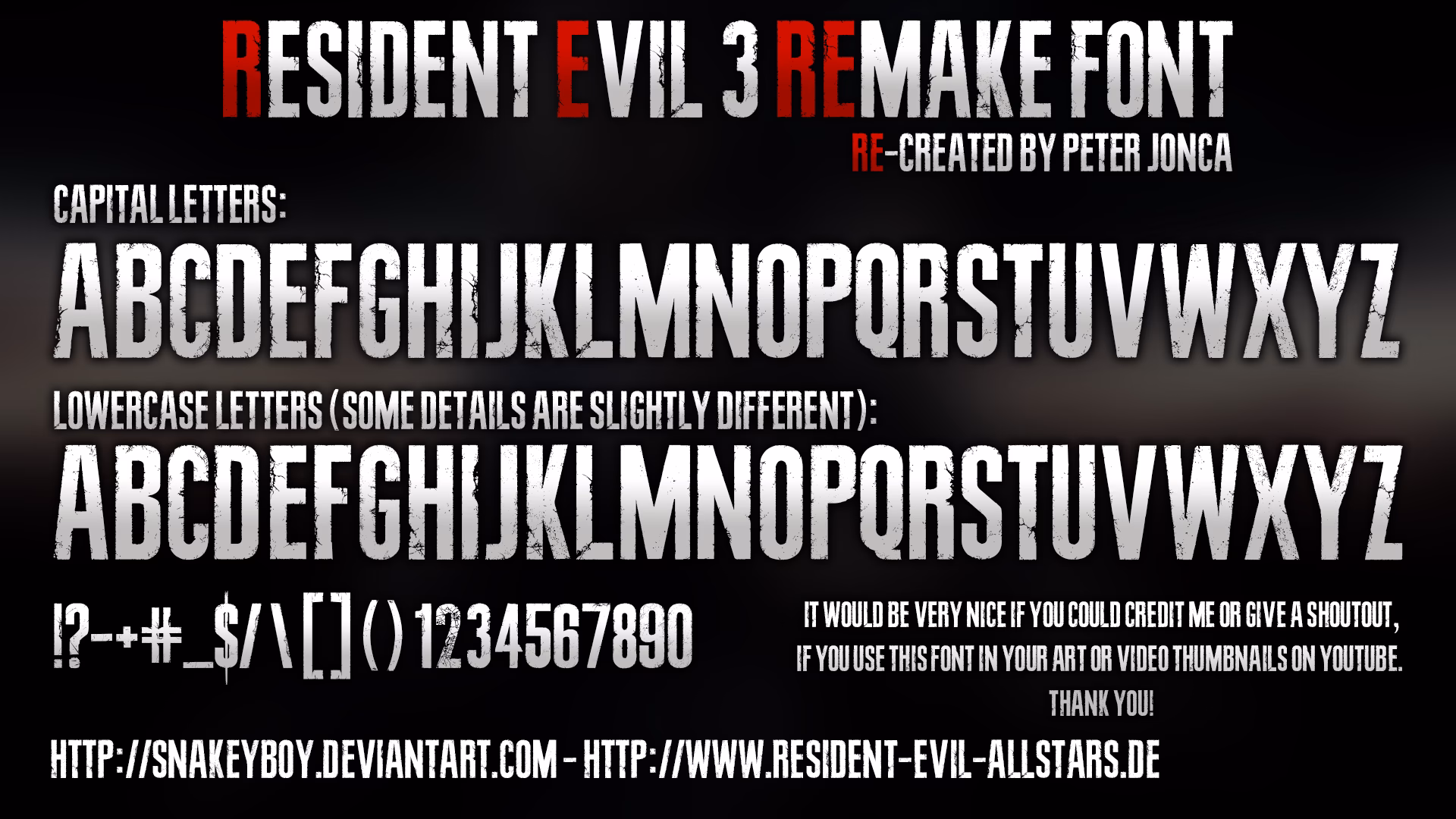
Tipografía y Terror en Resident Evil
Cuando pensamos en la saga Resident Evil, nuestra mente evoca inmediatamente imágenes de zombis, mansiones lúgubres y una tensión constante. Sin embargo, hay un elemento de diseño que, aunque a menudo subconsciente, juega un papel crucial en la construcción de su atmósfera: la tipografía. Las fuentes utilizadas en los logos, menús y documentos del juego no son meros adornos; son una herramienta narrativa que define el tono, evoca una era y sumerge al jugador en un mundo de pesadilla. Desde las afiladas letras del clásico de 1996 hasta los bloques opresivos de Resident Evil 7, cada elección tipográfica es una pincelada más en el lienzo del terror.
A lo largo de más de dos décadas, la identidad visual de la franquicia ha evolucionado, y con ella, su uso de las fuentes. Este artículo se sumerge en el fascinante mundo de la tipografía de Resident Evil, explorando cómo las letras y los símbolos han ayudado a dar forma a una de las series de videojuegos más influyentes de todos los tiempos.
El Legado del Logo Original: Nace un Icono
En 1996, Capcom lanzó para la Sony PlayStation un juego que cambiaría para siempre el género del survival horror. Conocido como "Biohazard" en Japón, "Resident Evil" en Occidente presentó un logo que se convertiría en sinónimo de miedo. La fuente utilizada, que muchos fans y diseñadores conocen simplemente como "la fuente de Resident Evil", es una recreación casi perfecta de ese lettering original. Su diseño es simple pero increíblemente efectivo: letras mayúsculas con serifas afiladas y puntiagudas, casi como garras, que transmiten una sensación inmediata de peligro y agresión.
Esta tipografía no solo adornaba la caja del juego, sino que establecía una promesa al jugador. Las ligeras irregularidades y el espaciado evocaban el estilo de los pósteres de películas de terror de serie B, un guiño a las inspiraciones cinematográficas de Shinji Mikami. Aunque la fuente en sí misma es relativamente básica, conteniendo solo el alfabeto en mayúsculas y minúsculas, su impacto fue masivo. Se convirtió en la identidad visual de la franquicia durante años, apareciendo en secuelas y spin-offs, y consolidándose en la memoria colectiva de millones de jugadores.
Un Nuevo Horror: La Ruptura Estilística de Resident Evil 7
Con el lanzamiento de Resident Evil 7: Biohazard en 2017, la saga experimentó un renacimiento. Volvió a sus raíces de terror puro, abandonando la acción desmedida de entregas anteriores. Este cambio drástico de tono necesitaba una nueva identidad visual que lo acompañara, y la tipografía fue fundamental en este proceso.
El logo de RE7 rompió por completo con la tradición. En lugar de las serifas afiladas, nos encontramos con una fuente sans-serif, estructurada, modular y en bloques. El diseño es frío, casi clínico, pero con un toque siniestro y de decadencia. La fuente más popularmente asociada con este juego, conocida como "Resident Evil 7 Regular", captura esta esencia a la perfección. Su aspecto geométrico y ligeramente desgastado parece sacado de una vieja cinta VHS o de la señalización de una instalación abandonada, encajando perfectamente con la estética de "metraje encontrado" y el entorno opresivo de la plantación de la familia Baker en Luisiana.
Este cambio no fue casual. La nueva tipografía comunicaba un tipo de horror diferente: menos cinematográfico y más personal, íntimo y perturbador. Es una fuente que transmite una sensación de encierro y de un mal sistemático y calculador, en lugar del caos monstruoso de los primeros juegos. La elección de este estilo fue una declaración de intenciones, señalando que este era un Resident Evil para una nueva generación, dispuesto a redefinir el miedo.
El Renacimiento de un Clásico: La Fuente de Resident Evil 4 Remake
La pasión de la comunidad de jugadores a menudo se manifiesta de formas creativas, y el diseño de fuentes no es una excepción. Con la llegada del aclamado remake de Resident Evil 4, los fans no tardaron en analizar y recrear su nueva tipografía. Un ejemplo notable es el de un creador que dedicó más de ocho horas a replicar la fuente del remake, incluyendo letras mayúsculas, minúsculas y símbolos.
La tipografía del remake de RE4 es un híbrido fascinante. Consigue evocar la esencia del original, con sus connotaciones góticas y su aire de misterio europeo, pero la moderniza con líneas más limpias y un acabado más pulido. Es un equilibrio perfecto entre nostalgia y diseño contemporáneo. Esta fuente refleja el propio juego: respeta el material original pero lo refina y lo adapta para una sensibilidad moderna, intensificando la tensión y la atmósfera sin perder su icónica personalidad. El hecho de que los fans inviertan su tiempo en recrear estos elementos demuestra el profundo impacto que tiene el diseño visual en la experiencia del jugador.